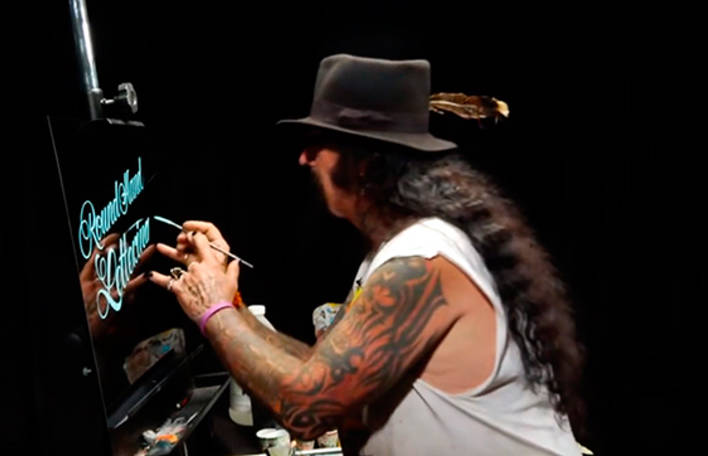
Depuis les années 70, où il faisait de la customisation typographique sur camions, voitures de course, logo, guitares et vélo, l’artiste auto-didacte Glen Weisgerber est passé maître dans l’art de la typographie peinte à la main. Dans cette vidéo il fait une démonstration de son talent de en expliquant les effets de courbes pleines et maigres.